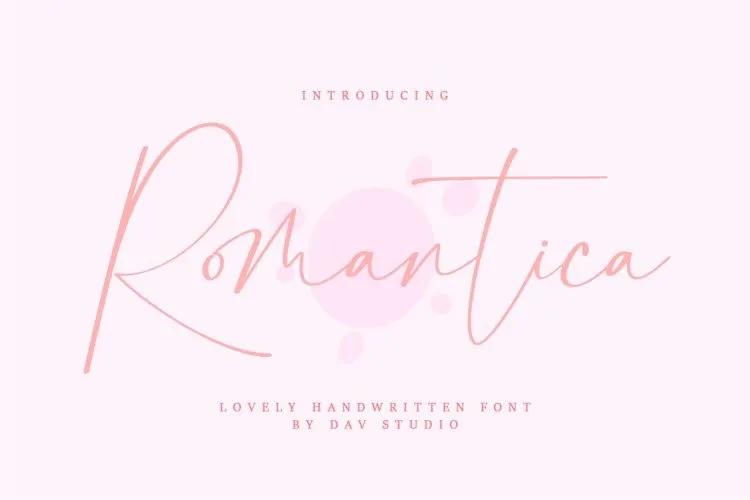
A Romantica Font é uma elegante tipografia de script feminina perfeita para aqueles que desejam um toque delicado em seus projetos DIY. Com suas curvas fluidas e traços elegantes, ela não apenas transmite sofisticação mas também a sensação de uma autêntica assinatura pessoal. Esta fonte é ideal para criar design inovador em aplicações variadas como cartões de negócios, convites de casamento ou vídeos no YouTube. Com ligaturas estándar para combinar com sua própria escrita à mão, a Romantica Font torna seu trabalho único e autêntico, oferecendo uma solução perfeita para criar designs que se destacam entre os demais.